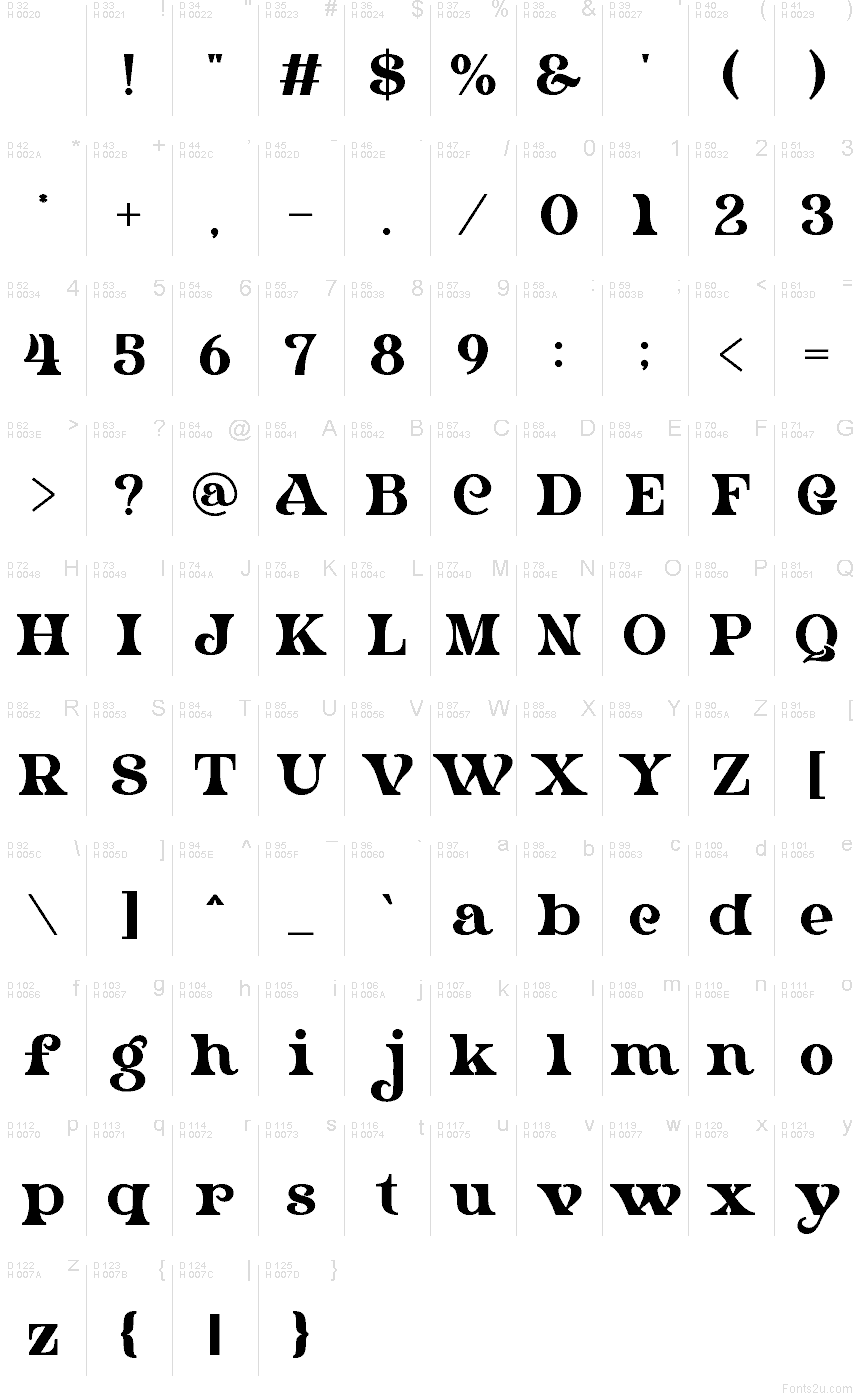
Vineca to darmowy, utrzymany w stylistyce retro font typu display od Ermedia Studio, emanujący teatralnym klimatem szeryfowych krojów z lat 70. Jego znaki łączą szerokie, miękkie łuki z ostrymi przejściami oraz figlarnymi detalami przypominającymi krople, co nadaje napisom bogaty, niemal ornamentalny rytm.